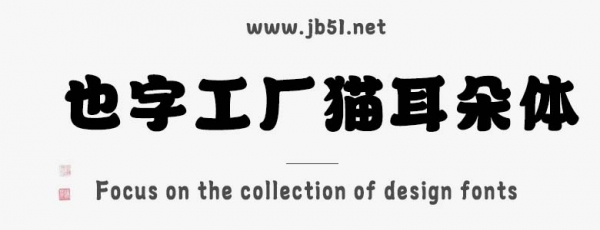
也字工廠貓耳朵體是由也字工廠出品的藝術(shù)字體 ,字體筆觸略粗,字形端正,俏皮可愛,具有很好的視覺感,適合應(yīng)用于藝術(shù)設(shè)計(jì)、平面宣傳設(shè)計(jì)、網(wǎng)頁(yè)設(shè)計(jì),書法字帖等領(lǐng)域。有需要的朋友快來(lái)本站下載使用吧。